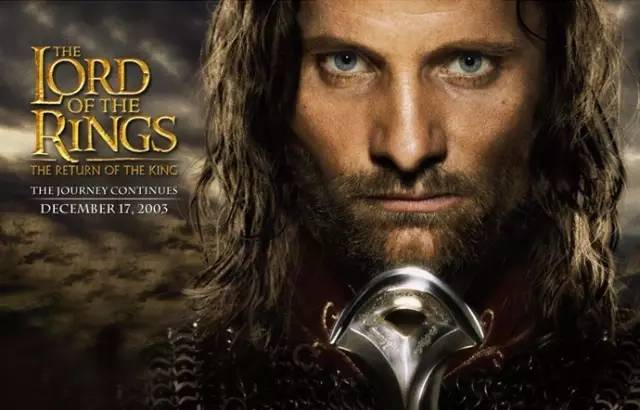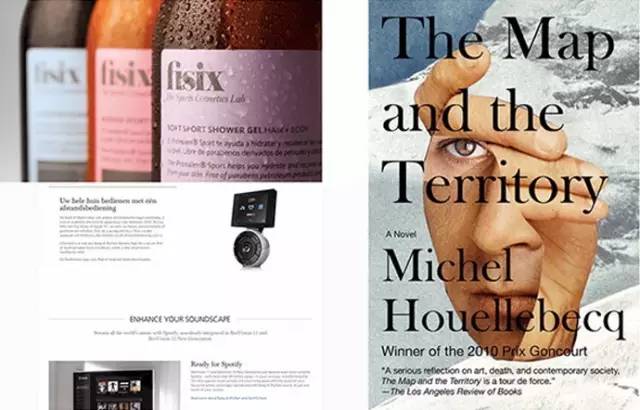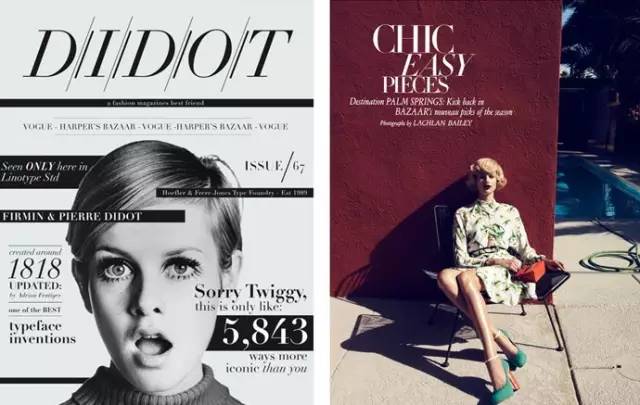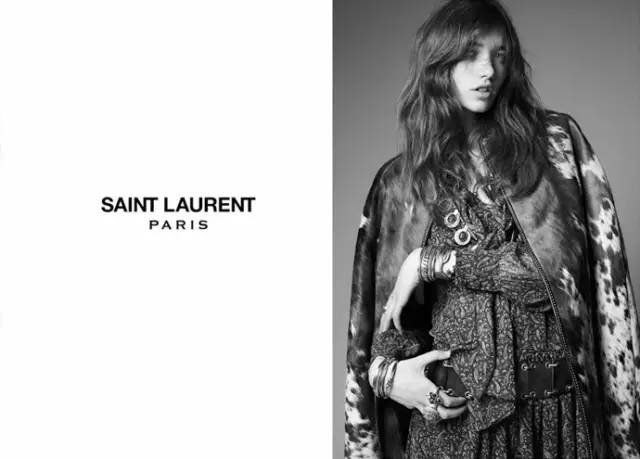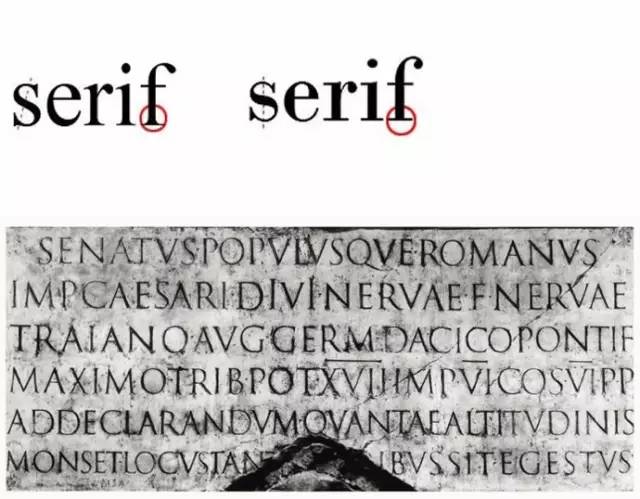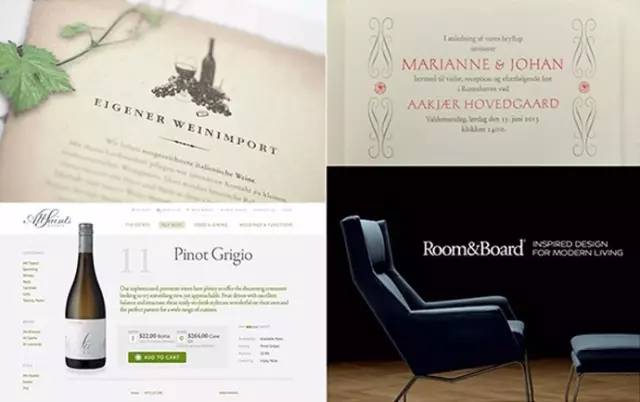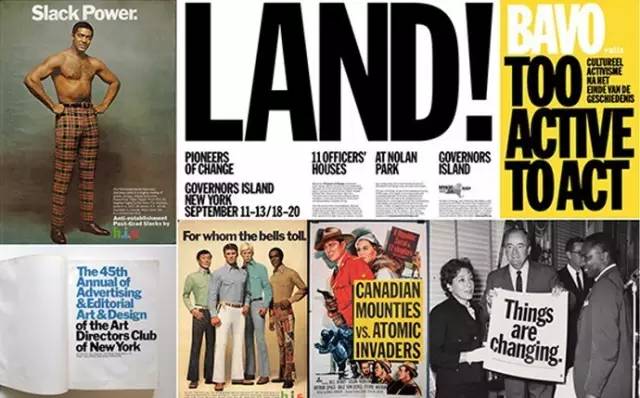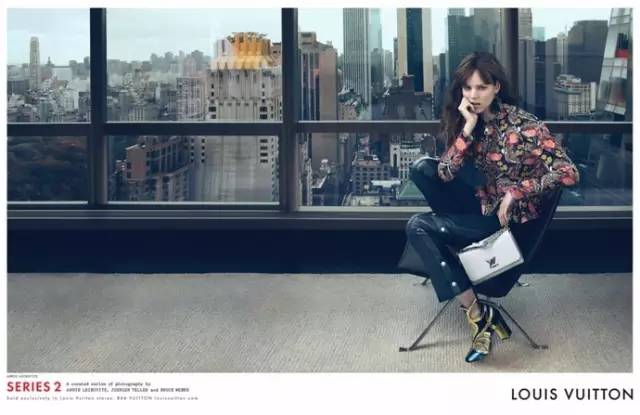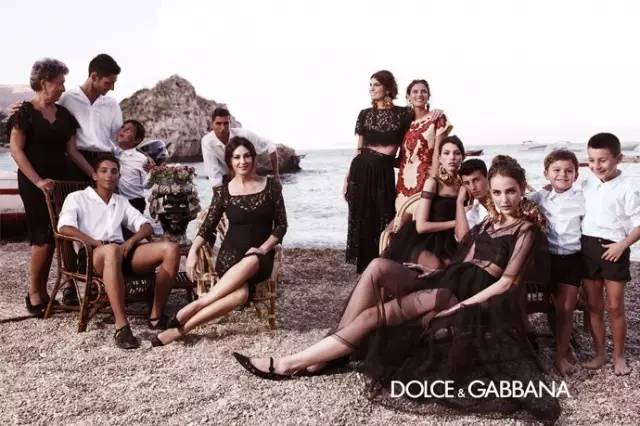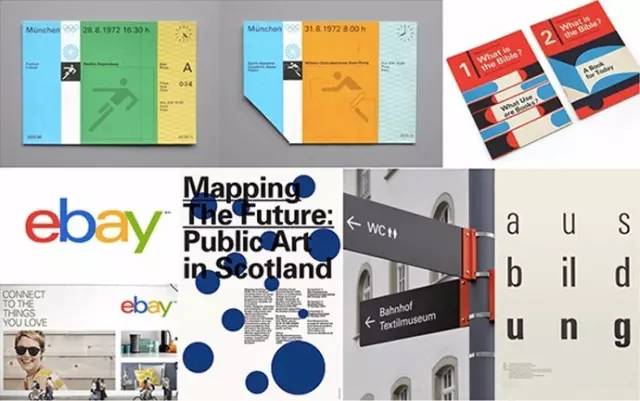
无衬线字体和衬线字体中的明星字体大全
好了,说正题。今天这篇出自腾讯设计师的文章,把无衬线字体和衬线字体中的经典明星款都列了出来,附上简单易懂的使用说明。不知道该用哪些字体?对字体不熟悉怕用错?来看看吧!
字体的分类有很多
罗马字体或衬线体(roman,serif);无衬线体(sanserif);手写体(script);雕刻字系(glayphic);典籍体字系(Classical);装饰体字系(decorative); 展示体字系(Display);当代字体字系(Contemporary);符号字系(Symbol) …今天我们主要讨论的是衬线体与无衬线体的一些明星字体。
衬线体
笔画末端付加油爪状或者线条叫衬线,据说衬线有助于水平方向的视线移动,所以小说等正文排版中会更多的使用传统造型的罗马字体。文艺复兴时期到巴洛克时期的老罗马体,18世纪后具有直线型衬线的现代罗马体。
Centaur
具有史诗般正统风格,特别适合用于表现年代悠久。具体排版时注意合字和老式数字的使用。威尼斯的圣马可大教堂的指示牌就是用的这款字体,营造出优雅的氛围。指环王的海报运用的就是这款字体,以其烘托其史诗感的氛围。
Garamond
诗歌般感觉的传统、柔软、纤细的字体,没有强烈个性,十分易于阅读,老式罗马字体的代表性字体
Caslon
美国独立宣言用字,是活字时代的大热字体。活字时代有一个说法:在犹豫不决的时候就用卡斯隆。说明其应用的广泛。
Baskerville
过渡期罗马体(旧体到现代体)的代表性字体,非常经典,给人古典、高贵的感觉。
Didot
现代衬线体,发丝衬线。特点是强烈的笔画粗细对比和水平衬线,时尚,现代,优美。也是被当今时尚行业所广泛应用的字体。VOGUE、BAZAAR、W、ELLE等杂志的logo都采用的这款字体。奢侈品牌ARMANI同样也是使用的这款字体。
Bodoni
与Didot类似,适合大字体表现,相对Didot来说硬朗一点。
无衬线体:
20世纪无衬线体开始被广泛应用,字形简洁,在苛刻的条件下也容易识别,因此多用于报纸字典的标题、户外道路指示牌等。
Helvetica
作为现代字体中的经典字体其被应用得非常广泛,并不缺乏关注。Helvetica是Neo-grotesque字体,结构严谨,没有情绪导向,提供着强烈的安全感,好像怎么用都不会错,这是个优势也是个劣势,当我们的设计有比较明确的受众群体或者设计对象有比较明确的气质的时候能够寻找到有同样气质的字体会是更优的选择。一些时尚品牌也较喜好此字体,凸显其品牌独立简洁的个性。
Franklin Gothic
这款字体是很早出现的无衬线体,所以带有古风,笔画粗狂有力,具有男性化感觉,适合表现强有力,也是招贴海报的常用字体。
Futura
Futura是拉丁语未来的意思,现代且具有几何特征,感觉是现在的主流大热字体,尤其是要突出时尚,设计感的时候可以使用。
制作过程中受到包豪斯运动的影响。是LV的商标用字,也是现在很多杂志的首选字体。
Gill Sans
英国风格的代表字体,具有古典风格的骨架,但是又有很强的科技感和未来感,字体外形偏几何,但是是humanist字体,相对futura会柔和一些。
Optima
有古典气息,笔画两端比较粗中间比较细,气质优雅。时代周刊的字体更换,雅虎2013年使用Optima作为全新标识的设计基准都证明了这款字体的热度。
Univers
Grotesque字体,比Helvetica更加简练。字体家族非常全面,所以搭配使用很方便。
Myriad
Humanist字体,很早就已经流行,随着苹果的广泛使用更加引人注目,笔画柔和简洁。
Avenir
字形简洁,现代,虽然也有几何特征,但是不失人情味。Avenir是法语未来的意思,对同样未来含义的Futura是一种挑战,放大x-height,降部拉长,使得文字的易读性明显提高。字体家族也很完整。